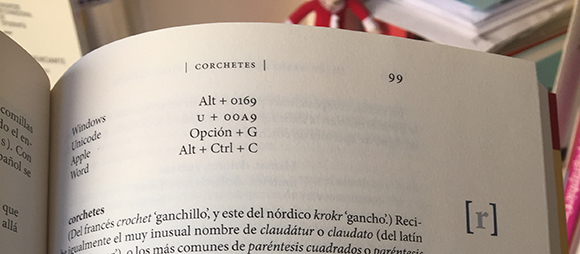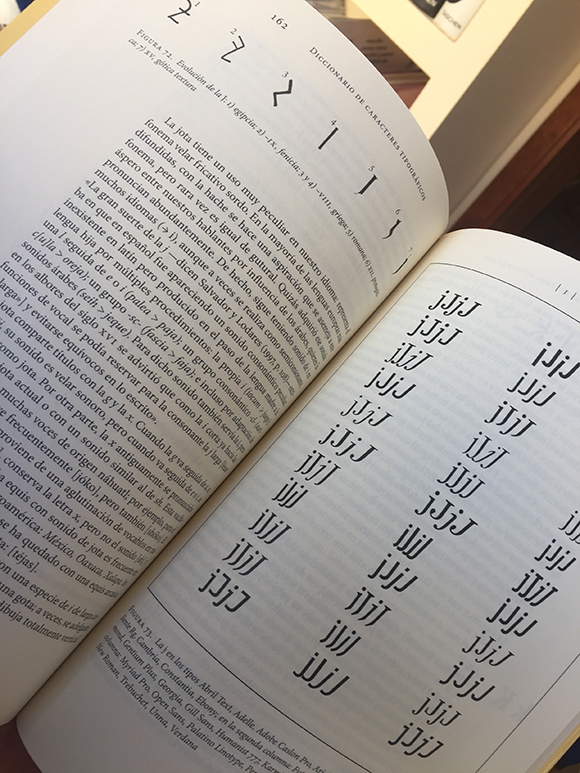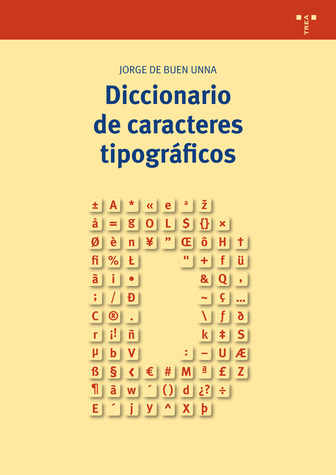
El tipógrafo y diseñador inglés Frederic Warde solía referirse a las letras como “estos pequeños signos arbitrarios” como si hubieran sido creados por un demiurgo con una mano caprichosa. Pero no, las formas de los signos tipográficos han sido moldeadas a través del tiempo por culturas diferentes que han ido incorporando a las mismas su contexto social, económico o político.
Por esta razón los signos tipográficos, cual si una muñeca rusa se trataran, guardan en su interior diferentes capas de significado o definición por lo que se hace imprescindible, para todos los que estamos interesados en ellos, conocer de primera mano su origen, evolución y convenciones de uso.
Y es aquí donde pongo sobre la mesa el último libro de mi admirado Jorge de Buen Unna, Diccionario de caracteres tipográficos. De Buen, autor, entre otros, del imprescindible Manual de diseño editorial que ya va por su cuarta edición, profesor universitario, conferenciante y experto en el campo del diseño editorial, tipografía y ortotipografía, emprende con este libro la tarea de organizar a modo de diccionario los diferentes signos tipográficos que podemos encontrar en las principales lenguas europeas.
Pienso que, como libro práctico que es, el formato de diccionario es el más adecuado ya que permite acceder a la información requerida de manera rápida y eficaz en las situaciones en las que generalmente se consultará, esto es, en medio de proyectos de edición, o simplemente al escribir un texto en nuestro ordenador y no estemos seguros de su utilización o configuración. Acompaña a la definición correspondiente a cada signo un repaso por su evolución a lo largo del tiempo y sus posibilidades de uso lo que amplifica sobre manera el valor del libro dado que no tenemos que recurrir a otras fuentes para obtener la más completa información sobre cada signo en cuestión.
Y no he podido abstraerme de curiosear al vuelo algunas entradas de signos como las comillas o los diferentes guiones para comprobar la precisión y profundidad de sus definiciones que hacen de este diccionario una herramienta indispensable para todo aquel que trabaje de forma intensiva con textos o incluso para el que simplemente sienta curiosidad por la historia de los signos tipográficos. En cualquier caso su lectura será práctica por un lado y enriquecedora por otro.
Diccionario de caracteres tipográficos
por Jorge De Buen Unna